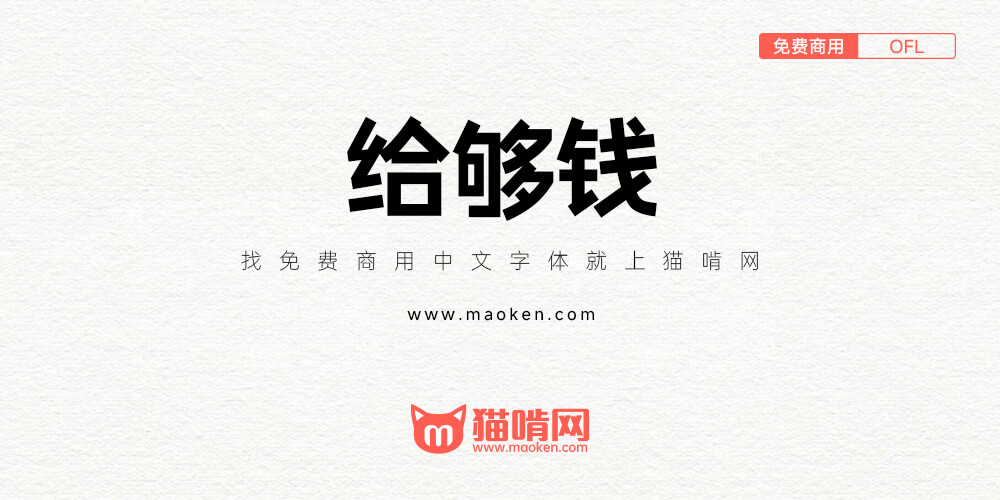
给够钱:吴杨峰出品比较硬朗的黑体 开放永久免费商用
给够钱体是吴杨峰出品比较硬朗的黑体,之前售价199元,现在吴杨峰决定把这款字体开放永久免费商用并委托猫啃网进行进行发布。
• 更新版本,版本号没有变,中英文略微调整了。
• 字体更新了新的对齐方式,更美观。
• 给够钱字体发布。
没人觉得 这字体跟mit授权的日本小夏黑体风格很像吗
方方先锋体平替(bushi
• 不不不,跟先锋细节完全不同,先锋太刻意都直,这个更方正,直但不呆板
这款字体霸气豪横,笔画简洁硬朗!这款字体你不会看到各种角度的斜角的收笔,正直、硬朗、结实!
嗯,不喜欢低于90度的尖角或转角,也不喜欢太多圆角,太柔,能直全直,即便不得以使用弧形也要硬朗的弧
非常好看的字体,很正,很方正,非常喜欢
This font’ s Alphabets arpe from Rodoto….
• does anyone know where the numerics are from?